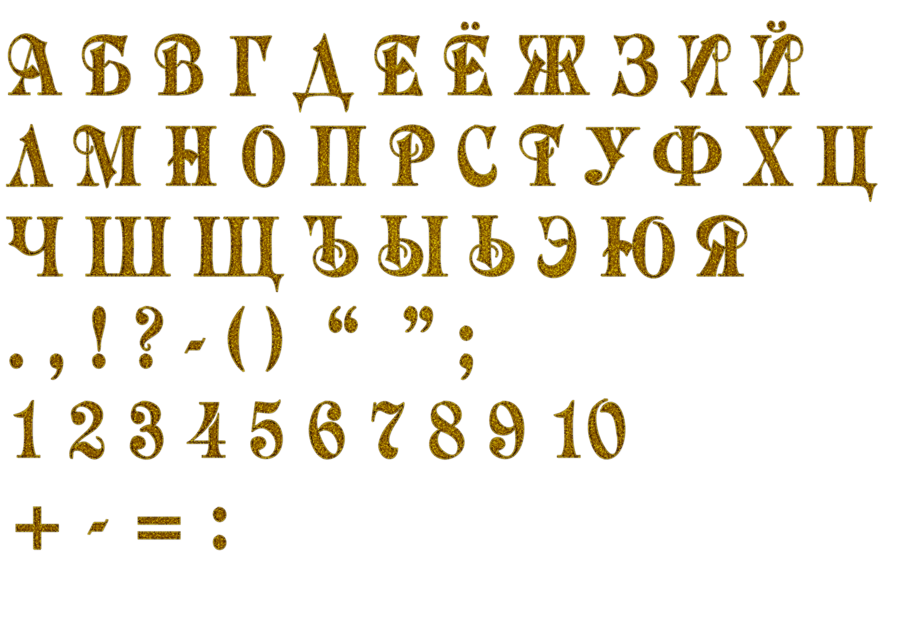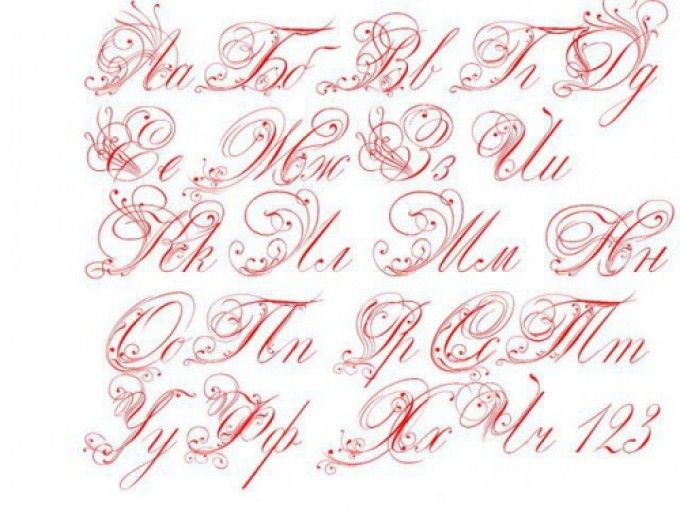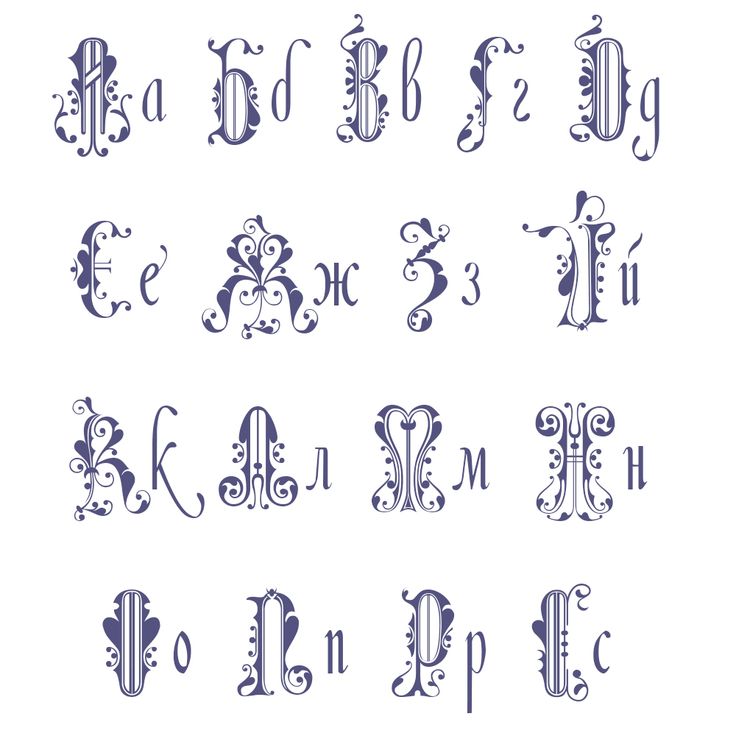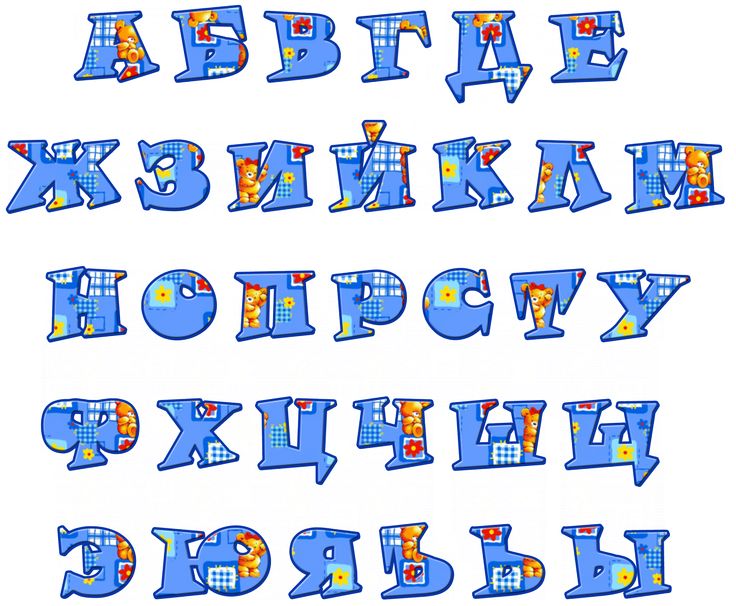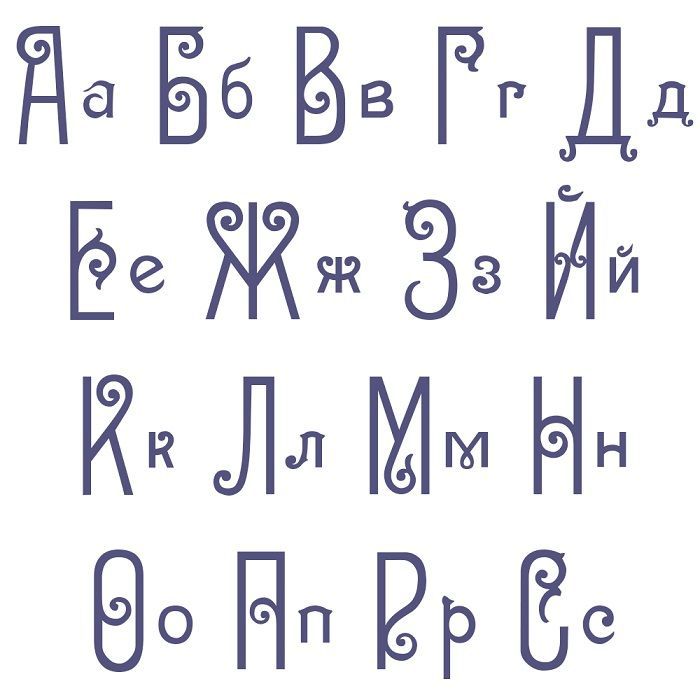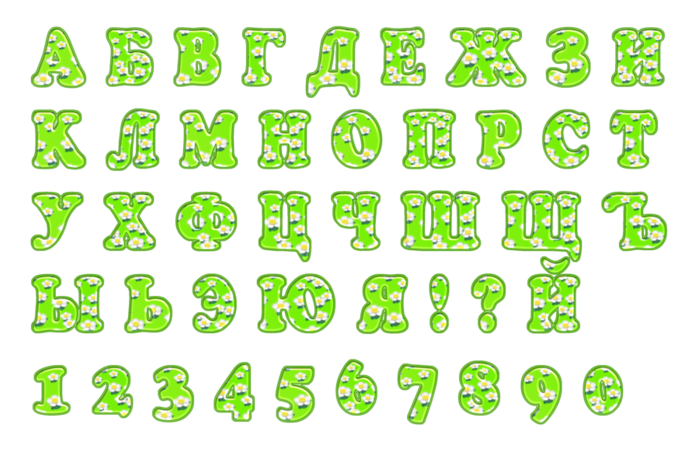
Русский алфавит красивые шрифты: Красивые буквы русского алфавита печатные и прописные для оформления плакатов, стендов, праздников, Дня рождения, Нового года, …
Шрифты являются важной частью любого дизайна. Правильно подобранный шрифт делает концепт стильным, качественным и законченным. Именно благодаря этой детали оформление смотрится законченным, а информация – уместной.
Почему не все шрифты подходят для русского алфавита
Многие начинающие графические дизайнеры сталкиваются со следующей ситуацией: потратив множество времени на поиск качественного и красивого кириллического шрифта, они скачивают, распаковывают и устанавливают понравившийся вариант, но русского алфавита в файле не находят.
Даже если на сайте указано, что в определенный набор кириллических шрифтов входит русский алфавит, это не значит, что он будет выглядеть красиво.
Поэтому перед тем, как загружать и распаковывать файл с набором кириллических шрифтов, необходимо убедиться, что:
- В этот набор входит русский алфавит.
- Русский текст, написанный этим шрифтом, будет соответствовать эстетическим представлениям пользователя.
На что нужно обращать внимание при поиске русских шрифтов
Выбирая красивый шрифт на русском, следует обращать внимание на следующие нюансы:
- Соответствует ли он своему назначению. Графические дизайнеры всегда обращают внимание на стиль шрифта и знают, подойдет ли он для определенной задачи. Приступая к поиску нужно заранее определиться, каким должен быть шрифт: уравновешенным и строгим или необычным и странным, классическим или современным, выразительным или читабельным.
- Какое количество стилей входит в одну семью (шрифтовую гарнитуру, комбинацию стилей под одним названием).
- Какое расстояние между буквами и между отдельными словами, сколько белого пространства.
- Контраст, насколько жирные вариации шрифтов жирные, а светлые – светлые.
- Насколько широкие буквы в верхней части, какая высота у их талии, легкий ли шрифт или массивный.
- Какая у шрифта форма: квадратная или круглая, закрытая или открытая.
- Входят ли в набор альтернативные начертания, соединения и символы.
Какие бывают русские шрифты
Все существующие на сегодняшний день русские шрифты можно разделить на три разновидности:
- С засечками. Засечками называют буквенные «подковы», которые придают шрифтам законченный и устойчивый вид. В прошлом их использовали для более качественного оттиска в процессе печати. Но сегодня многие убеждены, что засечки облегчают процесс чтения, не давая словам слипнуться в кашу.
- Без засечек. Такие шрифты часто называют гротесками, что буквально означает «причудливые» или «комически-уродливые». Они получили это название в качестве насмешки из-за их различий со шрифтами с засечками. Отличительной чертой гротесков являются ровные края букв, которые придают им современный и минималистичный вид.
- Декоративные. К этой группе относятся шрифты, использующиеся в декоративных целях (к примеру, граффити, рукописные или другие виды необычных шрифтов, с помощью которых создают логотипы и заголовки).
Также русские шрифты можно искать в Pinterest. Вбив в поисковую строку «красивый шрифт для Инстаграма на русском» или «красивый шрифт для ников на русском», блогер найдет множество соответствующих досок с подборкой хороших вариантов.
Выбор правильного шрифта позволяет пользователям наделять свои веб-сайты или профили в Instagram четкостью и ясностью. Текст, написанный неуместным шрифтом, не будет удобен для чтения.
Когда шрифт отвлекает внимание на себя, информация, которую он доносит, не усваивается читателями. Поэтому типографика должна быть понятной и читабельной.